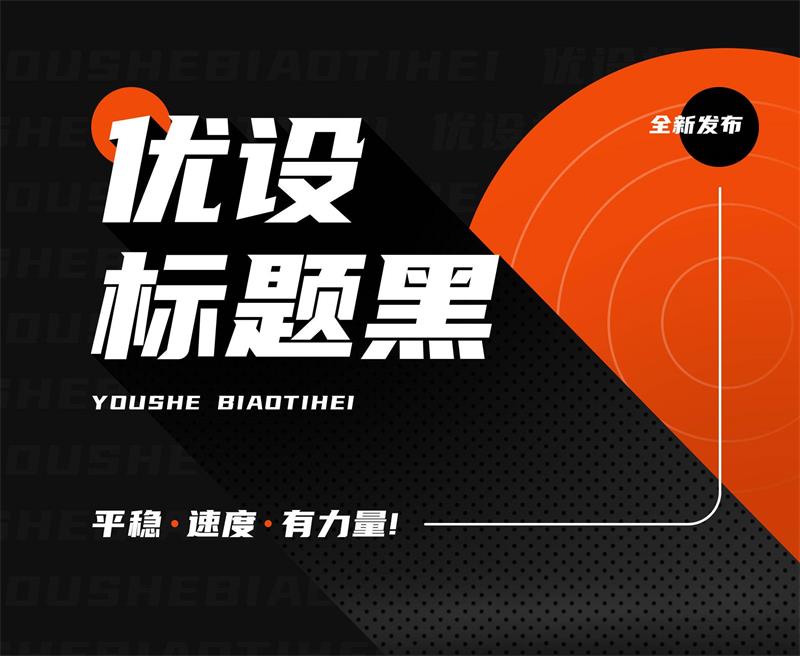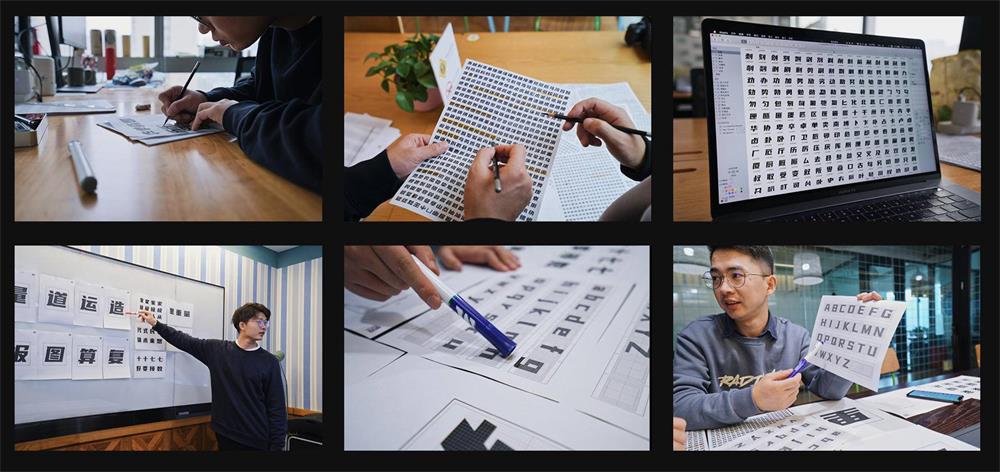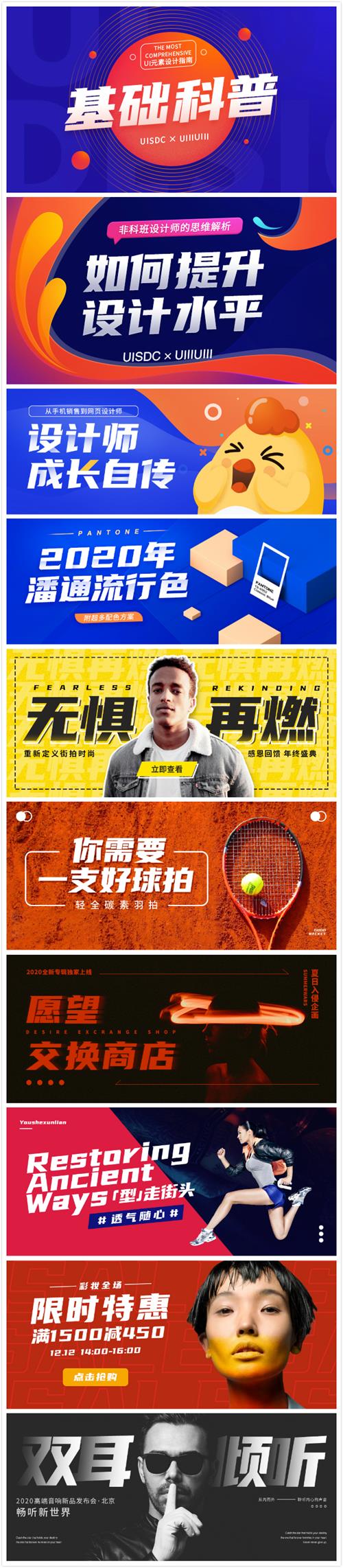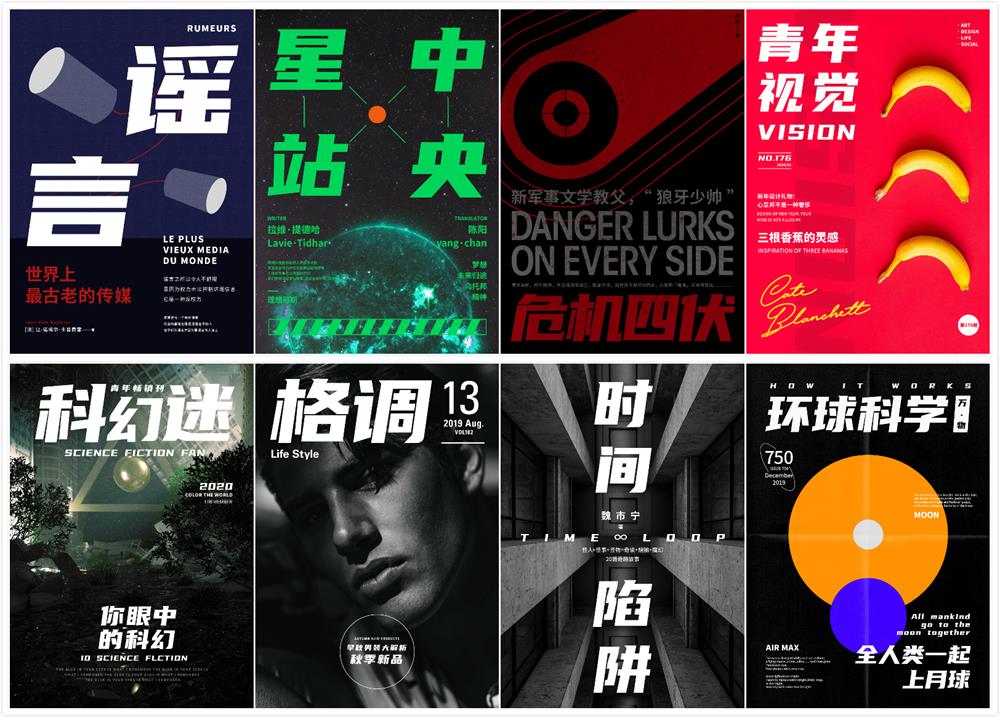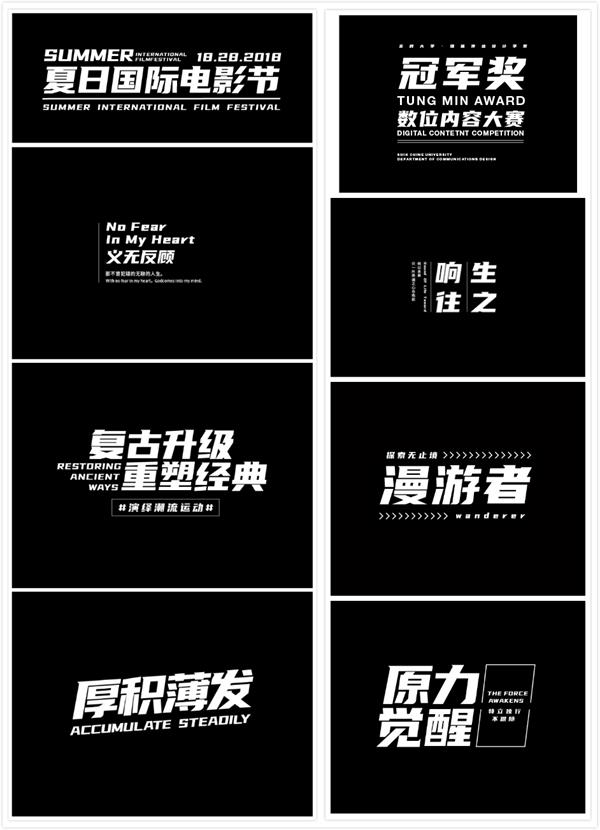
优设标题黑设计初衷
这两年为了给读者更好的阅读体验,优设网/优优网的首屏 Banner 都有专人设计,为了让图片更有设计感和冲击感,每一张图我们都重新设计了字体。
久而久之设计师发现,越来越多的广告标题字会使用这类倾斜的、粗壮的黑体字。但目前市面上这类中文字库少之又少,多数还是需要设计师现做,这会耗费大量的时间和精力。
所以优设一直在想,是否能专门做一款针对标题的中文字体,开放给全社会的设计师免费商用,让更多人受益呢?
在最初有了要制作一款免费商用字体的想法时,正好遇到字由的朋友,我们一拍即合,达成了联合发布优设免费字体的共识。为了保证字体顺利快速的发布,优设邀请字由联合参与并对字体的质量把关,在优设制定完 300 多个基础字型、字母及符号的创意与规范后,字由接手继续从字库角度出发,整体完善优化字型,完成了6000多个字型的制作,并用了大量时间来进行产品化和字体细节方面的优化。
历经 100 多天,不断推翻和调整细节后,这款包括 6763 个汉字和字符的「优设标题黑」终于在优设 8 周年之际,正式上线了!
优设标题黑字体特点
「优设标题黑」是一款适用性广,速度感、力量感极强的专业美术标题字体。
它以黑体字型为基础,整体字形沉稳,同时采用较大字面和粗壮的笔画来强化力量感。每个字体水平倾斜 8° 的设计,赋予了字体极强的速度感,为了让字体倾斜后也能保持稳固,设计师将整体字身设定宽扁。而起笔和弯钩上独具匠心的尖角设计,不仅突显了设计的几何感,而且方便后期修改。
所以这款字体,用在各类品牌广告和产品包装设计的标题上,最合适不过!
优设标题黑应用场景
Banner 篇:
海报设计篇:
书籍杂志篇:
文字组篇: